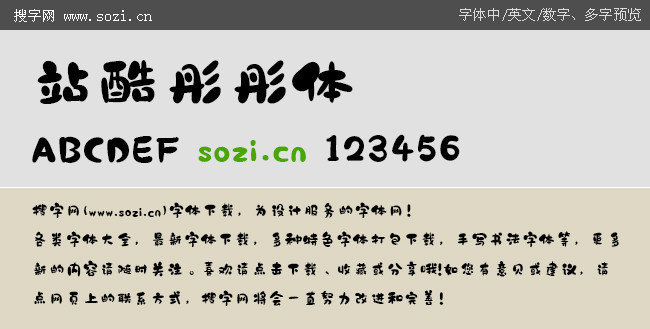
站酷彤彤體
搜字網(wǎng)提供一款站酷彤彤體中文字體下載,站酷彤彤體筆畫(huà)溫潤(rùn)活潑、憨態(tài)可掬、天真而浪漫。字和字之間、筆畫(huà)與筆畫(huà)之間的大小靈活變化,賦予字形獨(dú)特的節(jié)奏感和歡快感。本款字形適用于個(gè)性類(lèi)標(biāo)題設(shè)計(jì),廣告設(shè)計(jì),兒童讀物類(lèi)設(shè)計(jì)等應(yīng)用環(huán)境。。(此款為個(gè)人非商用版,如需商用請(qǐng)聯(lián)系作者購(gòu)買(mǎi))